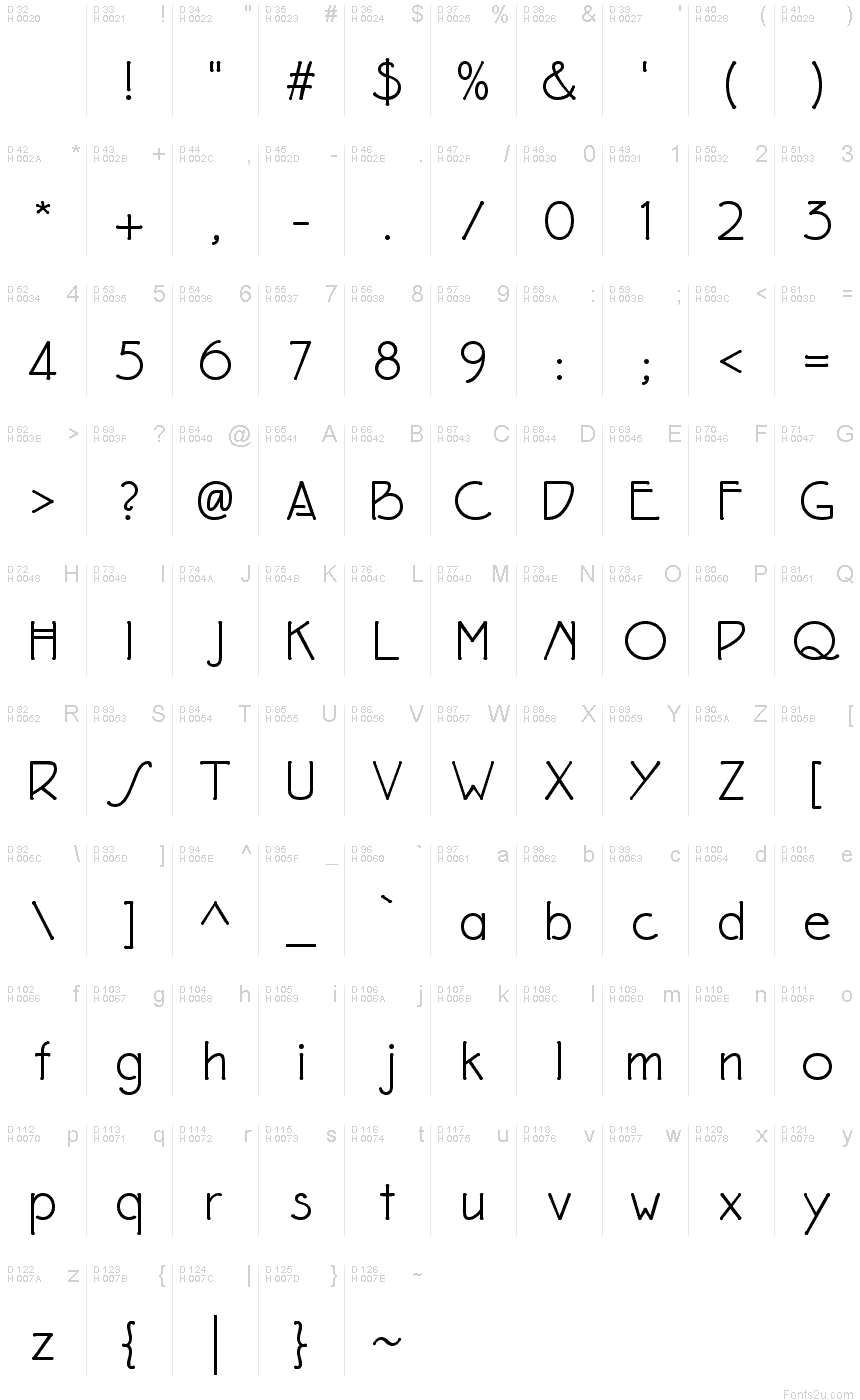
EaglefeatherFormalRegular
Eaglefeather Formal to darmowy krój pisma o bardzo lekkim, pełnym wdzięku charakterze i dopracowanym, ozdobnym stylu bezszeryfowym. Wysokie, wąskie kształty i gładkie linie nadają słowom formalny rytm, który jest elegancki, a nie sztywny, dzięki czemu idealnie sprawdza się, gdy szukasz czegoś wyrafinowanego, ale nie staromodnego.
Eaglefeather Formal świetnie sprawdza się w papeterii ślubnej, logotypach butików, opakowaniach kosmetyków, menu restauracji, okładkach książek, lookbookach modowych oraz czystych nagłówkach plakatów. Ten darmowy font ma w sobie grację i niemal ręcznie kreśloną miękkość, dzięki której litery płynnie się łączą. Zyskuje dzięki szerokim odstępom i dobrze komponuje się ze spokojnym krojem szeryfowym lub prostym bezszeryfowym w tekście głównym.